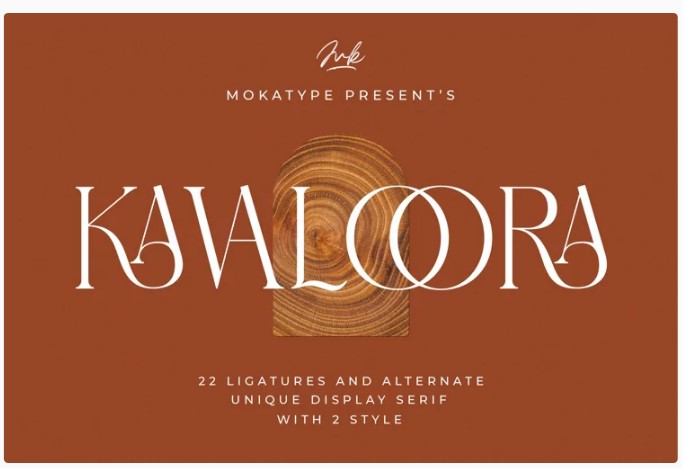
[Fontbundles] Kavaloora Font (2021)
Представляем Kavaloora - уникальный шрифт, использующий лигатуры для плавного соединения букв. Вдохновленный знаменитым минималистским логотипом, идеально подходит для целей дизайна шаблонов, брошюр, видео, рекламного брендинга, логотипов и многого другого. Идеально подходит для придания уникальной изюминки логотипам, монограммам или цитатам. Kavaloora имеет 22 уникальные лигатуры и альтернативные глифы, а также цифры и пунктуацию, что делает его супер фантастическим.